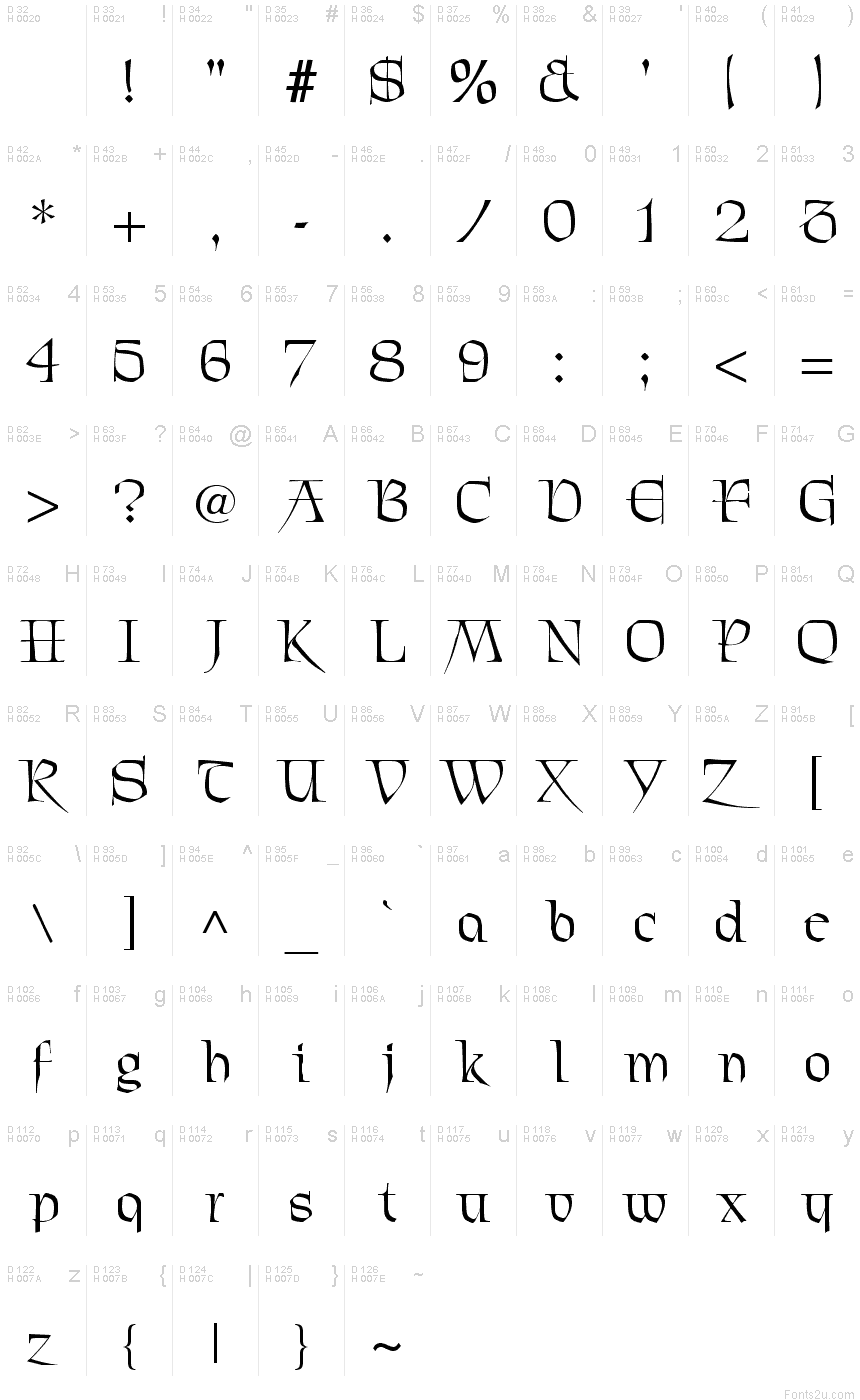
Patrick è un font decorativo serif caratterizzato da forme alte e calligrafiche, linee sottili, grazie a cuneo affilate e curve avvolgenti che gli conferiscono un tocco raffinato e leggermente d'altri tempi. I tratti fluidi e l'elevato contrasto rendono il logotipo nell'anteprima elegante senza risultare eccessivamente decorato.
Questo font gratuito è perfetto per loghi, partecipazioni di nozze, copertine di libri, packaging di boutique e titoli dove un carattere serif distintivo può dare carattere al design. Patrick Regular si adatta bene anche a poster ed etichette, poiché le sue forme strette e affusolate mantengono il testo espressivo e leggibile anche in frasi brevi.